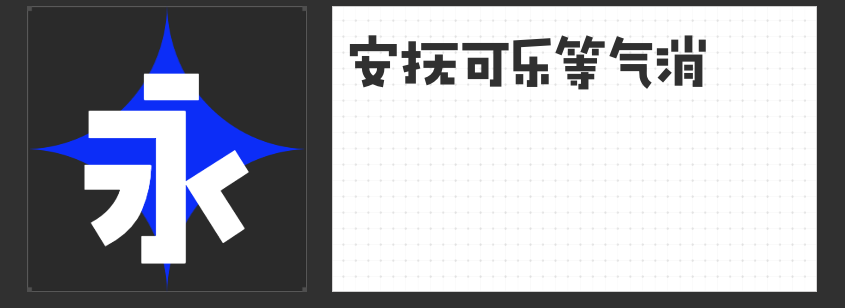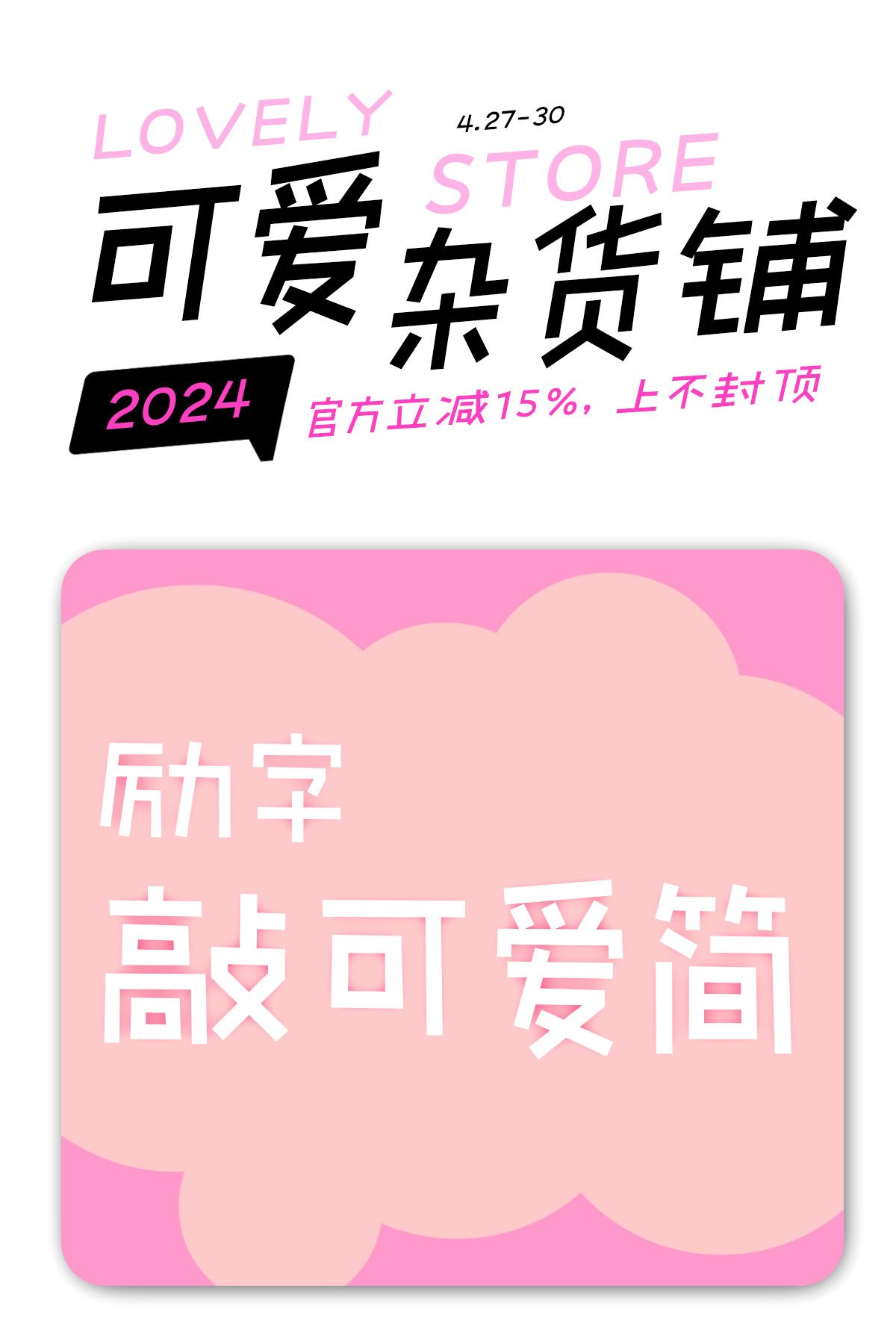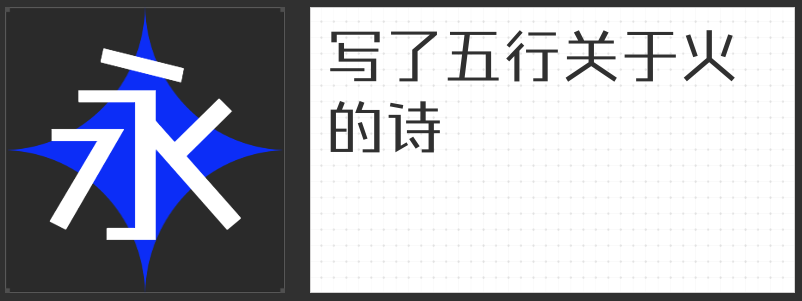
包装设计新宠:四款字库字体推荐
在包装设计中,字体选择至关重要。它不仅影响产品的视觉效果,还能传递品牌理念和产品特性。今天,为大家推荐四款适合包装设计的字库字体,它们各具特色,能够为你的包装设计增添无限魅力。
第一款推荐的是“字恋狂澄空 摇风”。这款字体以手写感为基础,字型上松下紧,重心略低,给人一种轻松愉悦的感觉。它的结构灵活多变,字面根据每个字的不同结构而发生变化,显得非常有趣。字间距安排合理,组合起来富有节奏感,非常适合用于包装设计的标题或标语部分,能够吸引消费者的注意力。
第二款字体是“励字志向黑简 大粗”。这款字体融合了圆体与黑体的特点,笔画拐角增加了适当的外圆角,使得整体字形稳重大气又不失灵动。它的字面充实,结构稳定,非常适合用于包装设计的正文部分,能够提升产品的整体质感。
第三款推荐的是“励字敲可爱简 中粗”。这款字体略带俏皮,充满趣味与想象。手写的圆润线条在保留辨识度的前提下,省略了部分笔画,使得字体更加简洁明快。它的独特形式营造了一种用心书写的随性,让字体更具手绘感,非常适合用于包装设计的装饰性元素,能够给消费者带来温馨的感受。
最后一款字体是“励字钧线黑简 常规”。这款字体具有完美的斜度和利索的转折,保持了独特的个性。它摒弃了过度的装饰,加强了细节的优化,使得阅读体验更加舒适。全直线的设计符合当代视觉审美,使得字体在包装设计中能够脱颖而出,成为画面主角。
以上四款字体各具特色,适合用于不同类型的包装设计。选择适合的字体不仅能够提升产品的视觉效果,还能更好地传递品牌理念和产品特性。希望这些推荐能够对你的包装设计有所帮助!